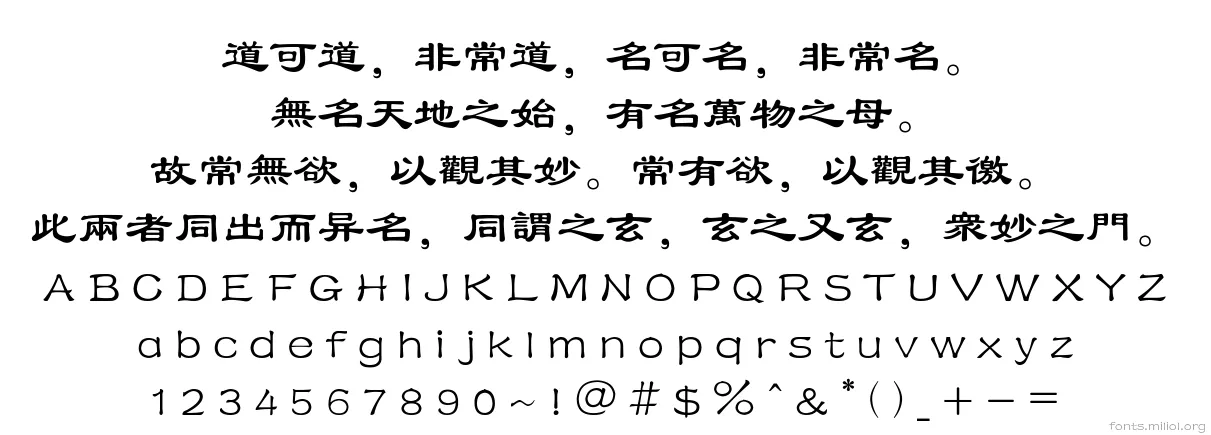
《方正隶书繁体 (FZLiShu-S01T) 字体赏析》
方正隶书繁体 (FZLiShu-S01T) 是一款兼具传统韵味与现代美感的书法字体,其设计灵感源自中国古典隶书,笔画浑厚端庄,结构严谨而不失灵动。该字体特别适用于文化宣传、古籍排版、艺术设计等领域,能为作品增添浓厚的文化底蕴。FZLSFW--GB1-0 是其标准编码版本,支持繁体中文显示,兼容性良好,可满足专业印刷与数字媒体的需求。
这款字体在细节处理上尤为考究,横平竖直间透出隶书特有的“蚕头燕尾”笔势,既保留了传统书法的神韵,又符合现代视觉审美。无论是标题设计还是正文排版,都能展现出独特的艺术表现力,是设计师与传统文化爱好者的优质选择。